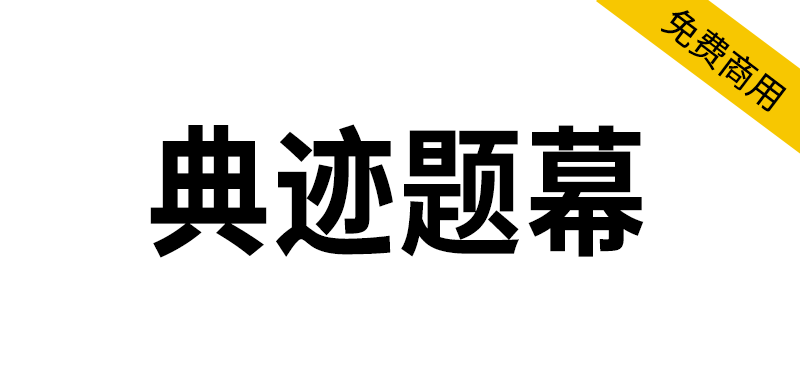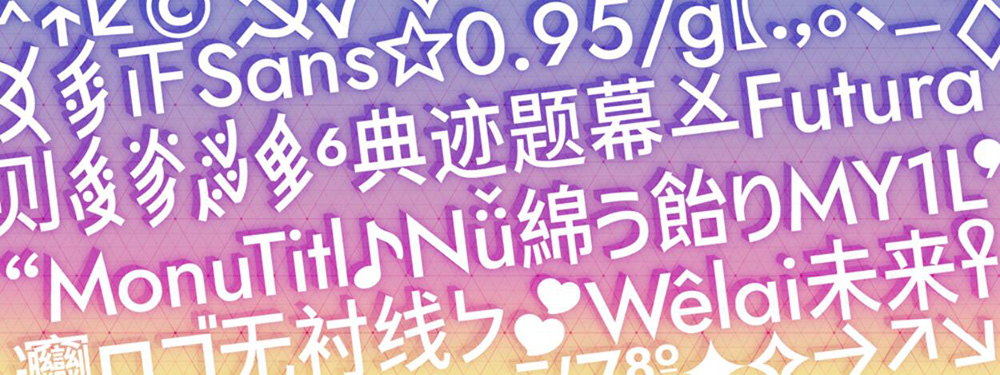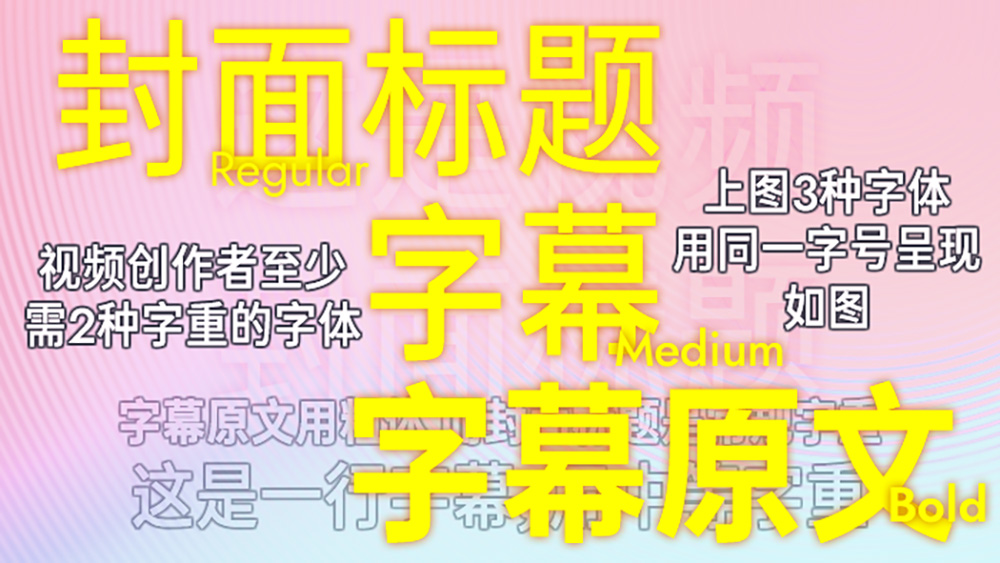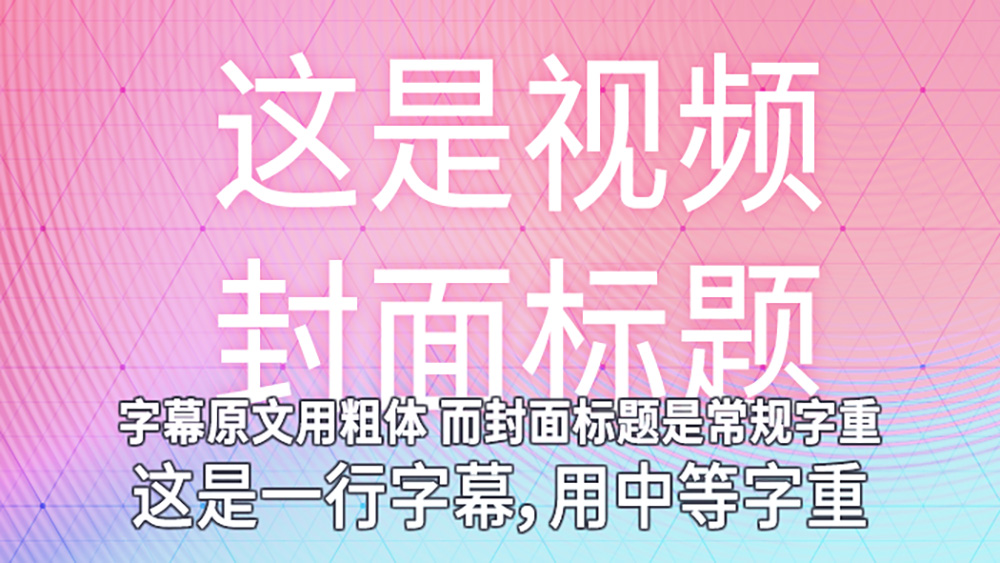
典迹题幕(MonuTitl)是一套为横排标题、字幕设计的女书窄黑体,Titl 是 (sub)title 的缩写,共3个字重(笔画粗细):窄体宜读(Condensed Book)≈常规 (Regular)、窄体中粗(Condensed Medium)、窄体粗体(Condensed Bold)。
所谓适宜标题、字幕,指字幕有不换行的需求,窄体更容易在一行里容纳一句话。为了看清字幕又需要它稍粗,但也不能是粗体,更不能是宋体等横细字体。因此即便你不考虑方正律师函,仅有常规和粗体的微软雅黑不适合做字幕。于是我做了这个完全 OFL1.1 授权的窄黑体,除了常规和粗体,还有介乎两者之间的中等字重。